文字の名前とグリフの名前04「グリフとCID」
グリフについて語る前に、もう一度「文字」の定義を確認しておきます。この連載はフォントの世界の話なので、単純に文字コード(具体的にはUnicode)の符号位置と紐付いているものが文字です。なので「辻」は二点しんにょうでも一点しんにょうでも同じ文字です。
でも、これらを区別して扱いたいときがあります。そこで登場するのが「グリフ」という概念です。実は「グリフ」には2種類の異なる定義があります。おそらくより一般的な説明は「文字の具体的な形」というようなものです。これはもちろん間違いではありませんし、わたしもそんなかんじの意味で「グリフ」という言葉を使うことがありますが、この連載では別の定義を採用したいと思います。「文字(character)とは別のレベルで区別される文字の形状についての抽象的な概念」くらいのかんじでしょうか。
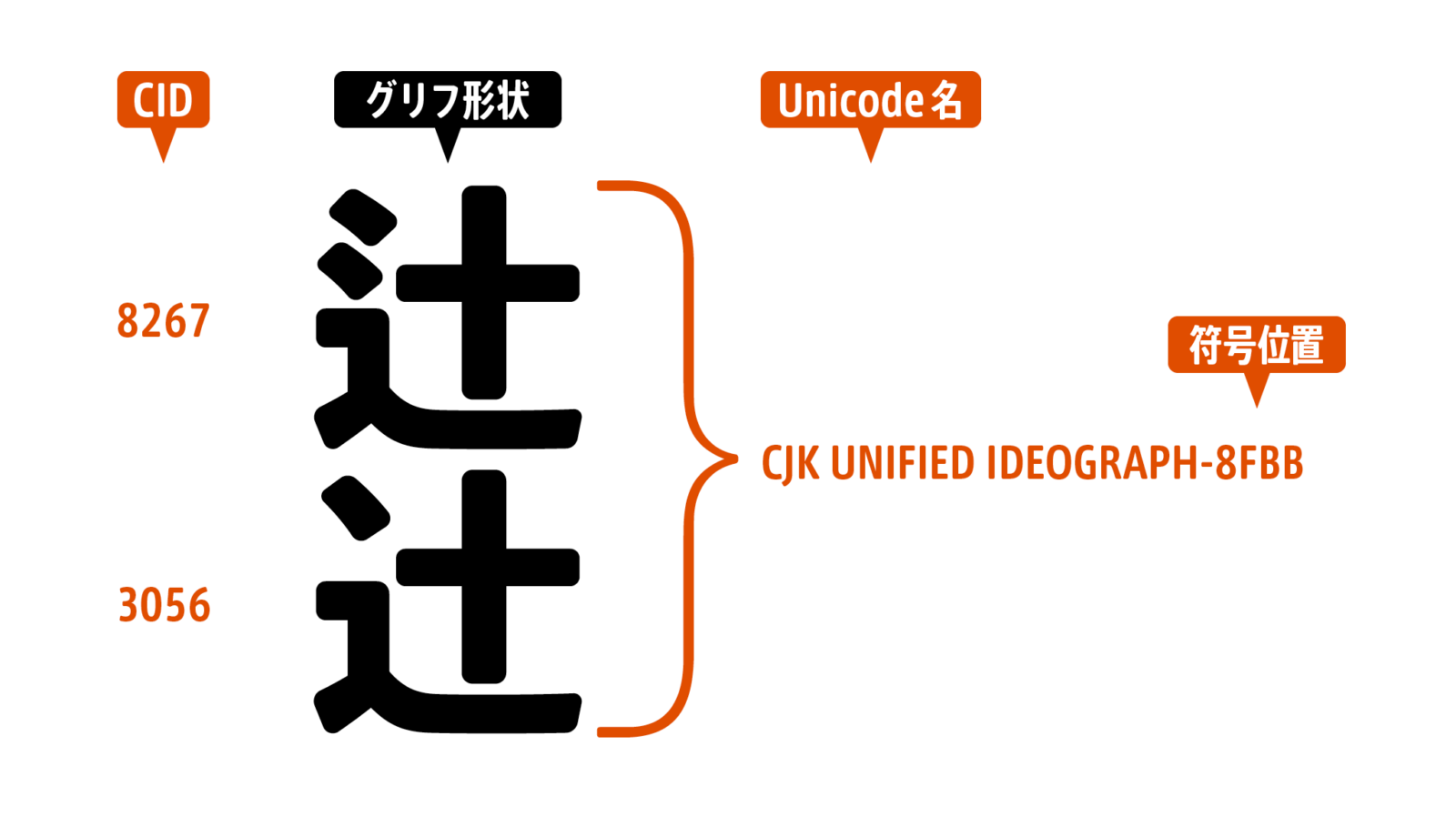
すみません。話が急にわかりにくくなりましたが、このあとすぐにわかりやすくなります。日本語OpenTypeフォントに収録するグリフについてはAdobe-Japan1という標準があり、グリフごとにCID(Character ID)という番号が振られていてます。Adobe IllustratorなどOpenType機能に対応したアプリケーションでは、これらを切り換えて表示することが可能です。
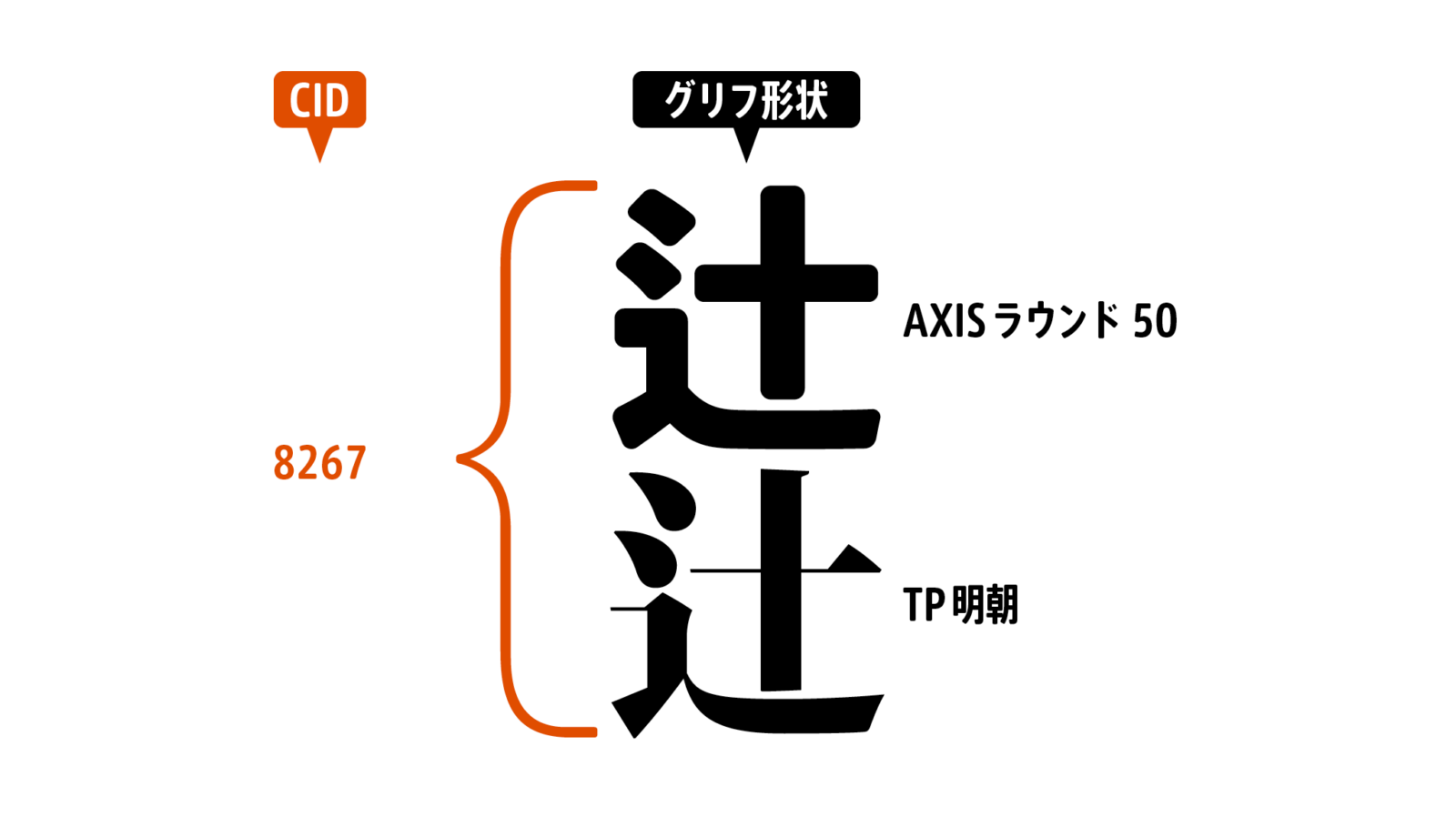
このような場合、グリフ標準のCIDと紐付いているものを「グリフ」と呼んでおこうということです。だから、AXISラウンド 50とTP明朝では、CID 8267(二点しんにょうの「辻」)の形はまったく異なりますが、同じグリフです。欧文フォントについては次回。